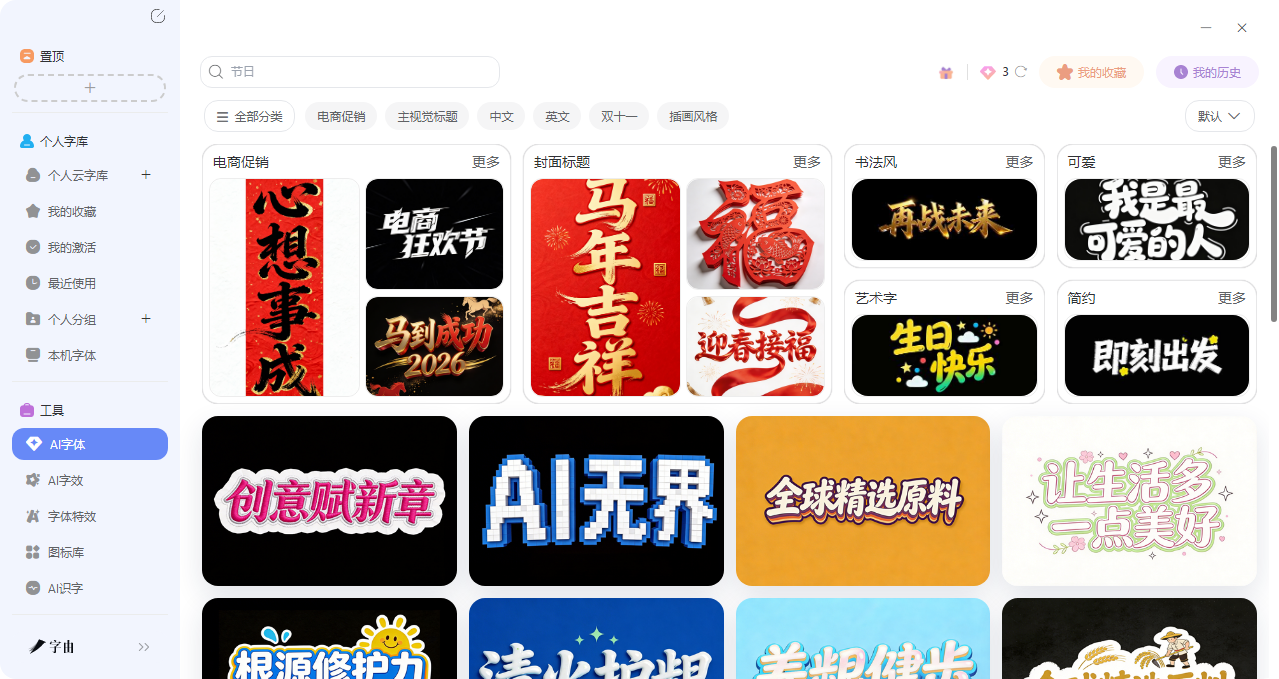
免费logo设计生成,这5个工具自己就能搞定
不论你是创业开公司还是在做自己的小品牌,那么设计专属于自己品牌的logo 绝对是不能避免的一个内容。但是如果请专业的设计师,好处是能有一个高质量的设计,坏处就是会因为预算不足而头疼,这对预算有限的小团队来说确实吃不消。但是,好在现在有很多能够免费 logo 设计生成工具,只需要自己动动手也能够设计出一个不错的 logo ,那么今天我就自己筛选了 5 款亲测可用的平台,每一款我都会写明使用感受和功能特色,快来一起看看吧!
第一个要推荐的免费 logo 设计生成工具,可能很多人没想到——字由。大家印象中的字由是字体管理神器,但其实它的 AI 字体功能,也能帮你搞定 logo 设计。
先来说一下字由里可以免费设计logo 的工具,那就是AI 字体功能,可以直接用来做logo 文字设计。你不需要会 PS,也不用懂复杂的设计软件,只需要以下几个步骤:
- 打开字由客户端,找到【工具】下的【AI字体】
- 浏览各种字体模板(电商促销、LOGO设计、Banner设计等分类)
- 选中喜欢的模板
- 输入你的品牌名称或文案(最好和模板字数保持一致)
- 点击“立即生成”,等30 秒左右就能得到设计好的 logo 文字
而且从图中也不难看出,字由支持的风格非常全面,发光字、镭射字、毛笔字、可爱风、卡通字、书法字、彩色字体……常用的基本都有。对于需要快速出LOGO文字方案的设计师来说,这个功能很实用。
再加上字由可以支持个人云字库,如果你有多版设计方案需要多个字体,那么字由的个人云字库可以上传你收集的字体,也十分便捷。
今天介绍的这5 款logo 设计工具各有各的优势,Turbologo AI 生成速度快,口碑好。LogoMaker 支持修改优化,还能对接人工服务。Smashing Logo 有着不用注册就可以直接生成的大优点,DesignEvo 模板库超大规模,几乎覆盖所有行业。但是我目前用得最顺手的还是字由,除了logo 设计质量高、产出速度快以外,还有就是平台每天会免费给算力点。其他的平台下载需要付费,但是字由不需要,除非你有大量的需求。做 logo 这方面它确实帮了我不少忙。如果你也感兴趣的话也来字由试试吧!